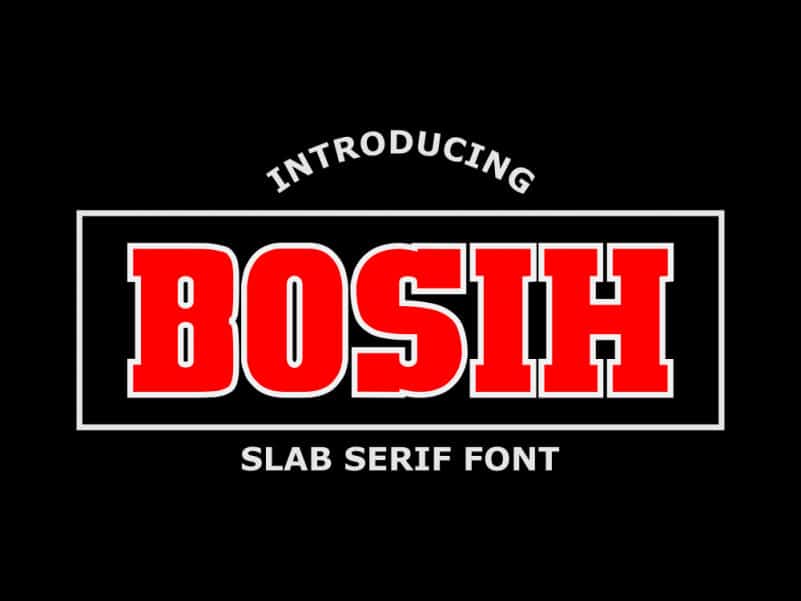
Bosih Slab Serif Font
Bosih Slab Serif Font terlihat berani, namun canggih dan menampilkan karakter tebal dan panjang yang akan terlihat sangat mahir saat digunakan dalam logo, branding, desain kemasan, dan banyak lagi. Font tampilan yang dirancang dengan ahli ini adalah benar-benar harus dimiliki. Ini berisi huruf besar, angka, tanda baca, simbol, dan dukungan multibahasa